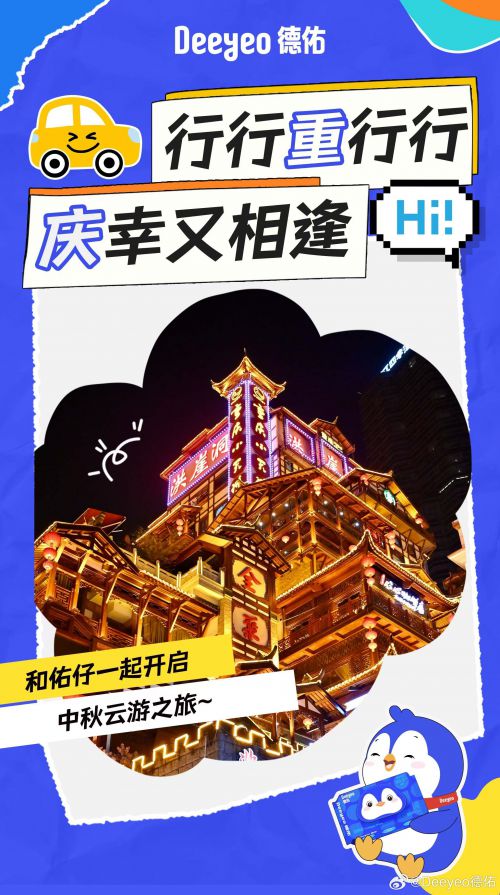
点字拙然体
【点字拙然体】是由点字库推出的创意卡通字体,兼具现代趣味与古拙韵味。字体以方正结构为基底,重心沉稳居中,中宫布局疏密得当,配合向右上微倾的笔画走势,既保留黑体的稳健基调,又通过倾斜角度注入活泼韵律,整体呈现出敦厚而不失灵动的视觉张力。 点字拙然体笔画设计独具巧思:粗细均匀的线条搭配圆润笔触,在起收笔处形成饱满圆弧,笔画间适度留白的断开处理,既增强字体呼吸感,又凸显卡通字体的稚趣特质。配合线条自然的渐变过渡,成功塑造出"拙中藏巧"的独特气质。 凭借多字重设计与完整的常规字符集,点字拙然体适用于文创设计、品牌IP塑造、儿童读物、短视频标题等多元场景,既能传递轻松活泼的品牌调性,又可通过稳健的骨架支撑正式应用需求,是创意与实用性兼备的商用字体选择。